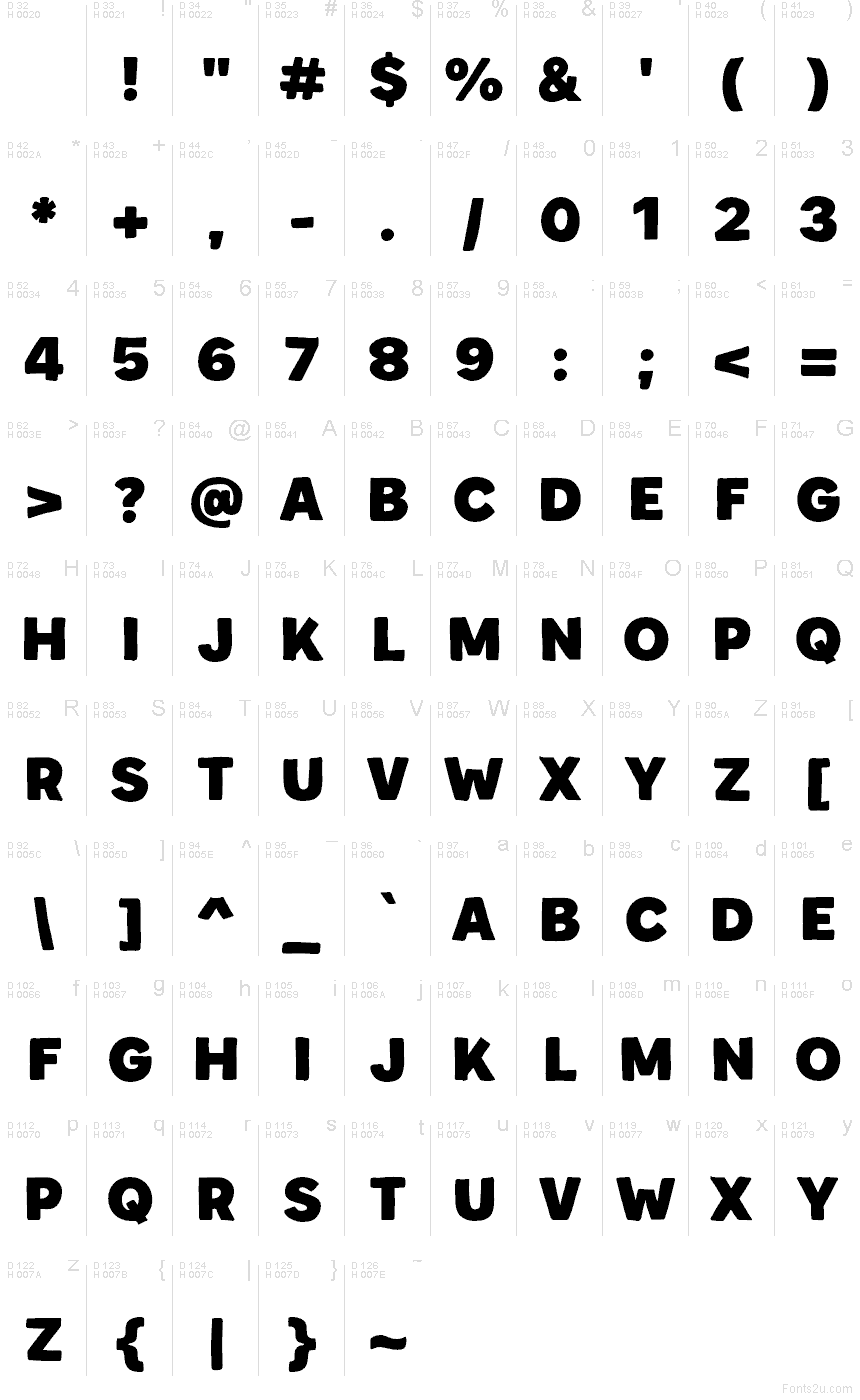
Fruity Kiwi de MJType es una tipografía de estilo cartoon gratuita y de visualización, construida con formas de letras anchas y pesadas que presentan una alegre irregularidad artesanal. Sus esquinas suavemente redondeadas y sus bordes ligeramente irregulares evitan que las mayúsculas sólidas parezcan mecánicas. Los trazos son mayormente uniformes, pero pequeños cambios en el grosor le dan a las letras una calidad ligera similar al papel recortado.
Los diseñadores que trabajan para marcas infantiles, de entretenimiento familiar o de alimentación informal pueden utilizarla en envases, pósteres y merchandising, donde las formas sobredimensionadas resultan amigables y directas. Esa misma combinación de masa robusta y trazo irregular hecho a mano también se adapta a gráficos de juegos y señalización de eventos, vinculando temas lúdicos con letras que parecen hechas a mano en lugar de tipografiadas.